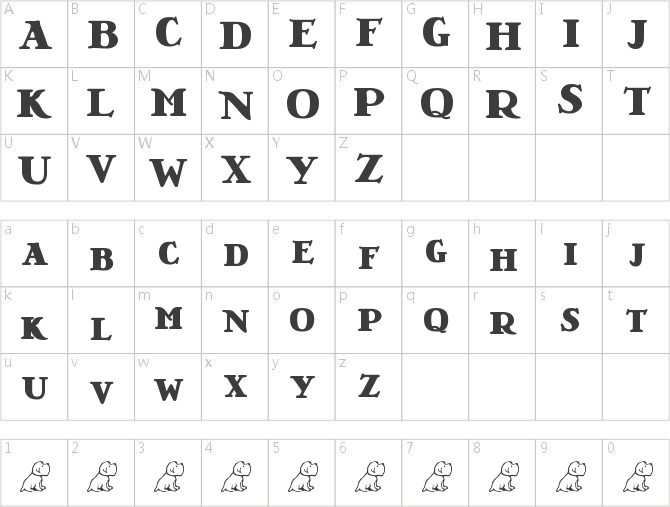
LRT Nutshell Library Black
LRT Nutshell Library Black介绍
LRT Nutshell Library Black字体字库是一款让人赏心悦目、百看不厌的英文字体,适合各类广告和产品包装设计应用,字体大小0.04MB,格式为ttf字体,上传用户是shiqiuping,作者/版权方为未知
LRT Nutshell Library Black效果图